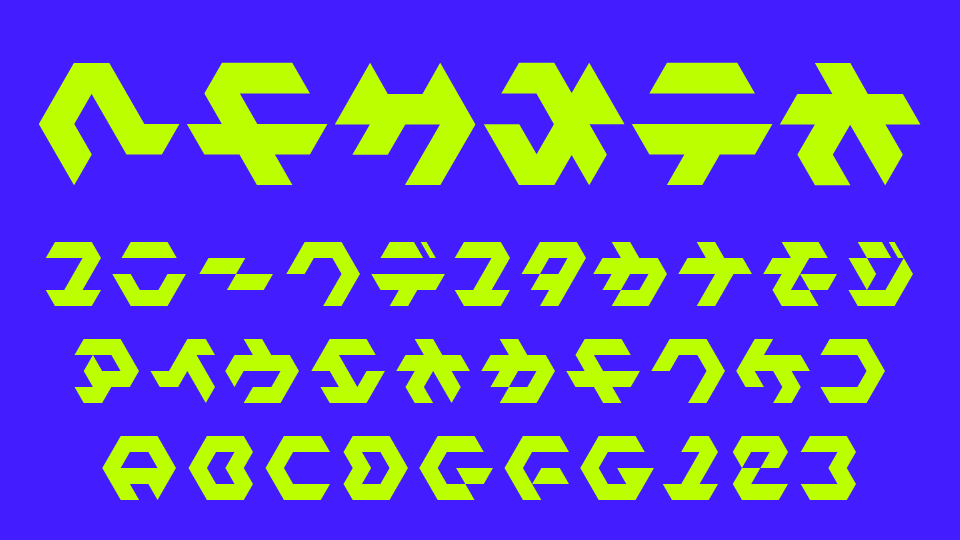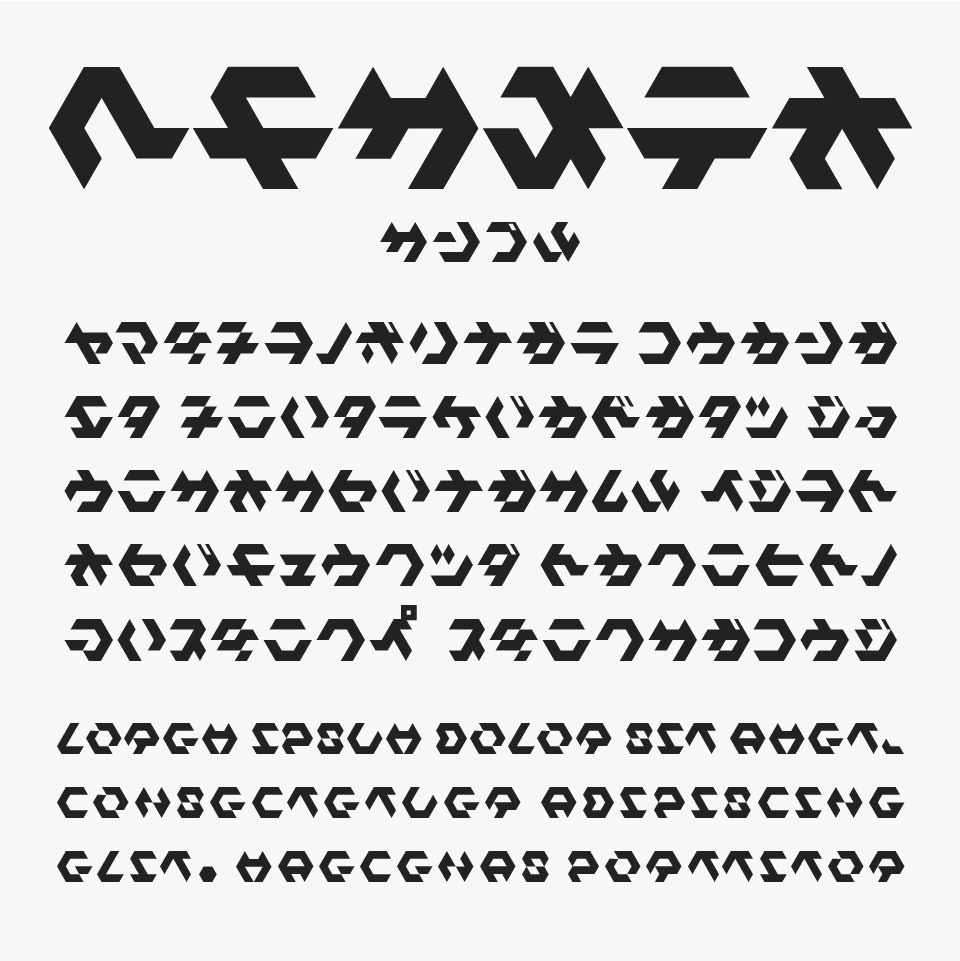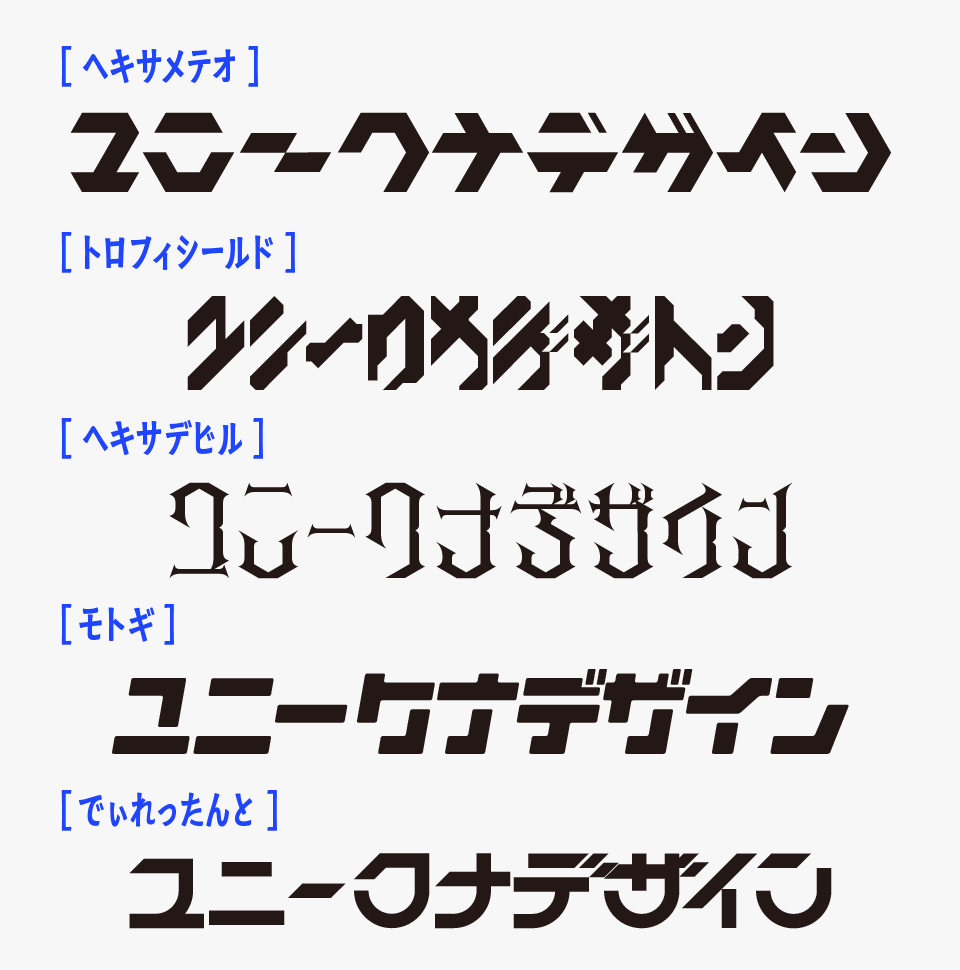
ヘキサメテオ
ヘキサメテオフォントは、六角形のパーツで構成されたユニークで近未来的なデザインカタカナフォントです。
文字の輪郭が六角形でデザインされており、まるでSF作品に登場する人工言語やテクノロジー企業のロゴのような雰囲気があります。日本語はカタカナのみの収録ですが英字ともに統一感が高く、文字の情報を伝えるというよりも世界観を演出するためのロゴにぴったりなフォントです。
サイバー、ロボット、宇宙開発、メカニカルデザインなどのテーマと相性が良く、タイトルやロゴに使うだけで一気に未来感を演出できます。鋭いエッジと独特な字形によって強いインパクトを生み出しながらも、規則性があるため画面全体が散らからないのも魅力です。
Hexa Meteoフォントを、ほかの幾何学的なスタイルを持つカタカナフォントと比較してみると、SF的でテクノロジー感のあるデザインに仕上がっているフォントです。
比較フォントは、「トロフィシールド」「ヘキサデビル」「モトギ」「でぃれったんと」と使用していますが、どれもユニークなフォルムをしたデザインフォントなので、ぜひあわせてチェックしてみてください。
収録文字は、カタカナ・アルファベット・一部記号が収録されています。